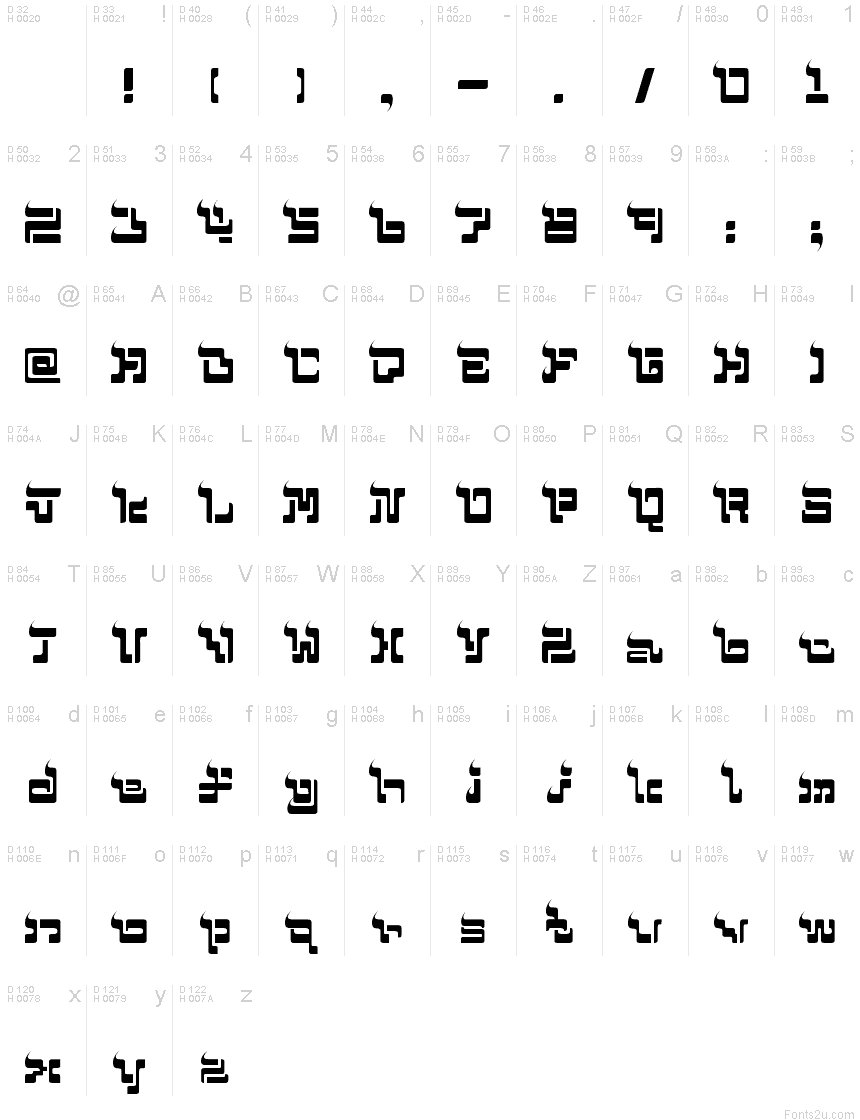
Mohammed to darmowy hebrajski krój typu display o kwadratowych, masywnych formach i zawijanych kreskach, które rozszerzają się na końcach. Litery sprawiają wrażenie zbudowanych z twardych, czarnych kształtów o zaokrąglonych narożnikach, a kilka wyższych kresek wznosi się w ostre haczyki, co nadaje linii rytualny, dekoracyjny rytm.
Mohammed to darmowy font na plakaty, logotypy, napisy tytułowe, etykiety produktów, ulotki okolicznościowe i wszędzie tam, gdzie hebrajska stylistyka wymaga wyrazistego, ornamentacyjnego sznytu. Połączenie solidnych bloków i płomienistych krzywizn świetnie sprawdza się w krótkich tekstach o graficznym charakterze, dzięki czemu font idealnie nadaje się do projektów kulturalnych, oprawy graficznej albumów oraz dekoracyjnych nagłówków.